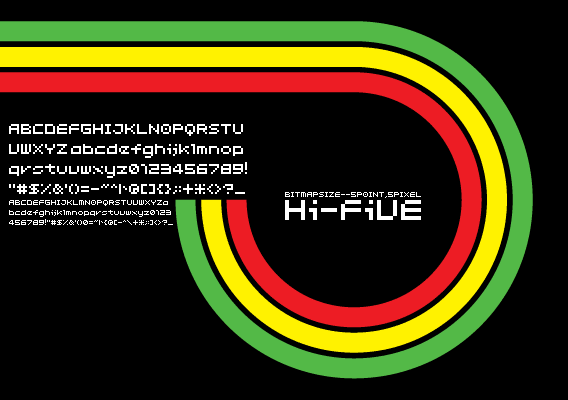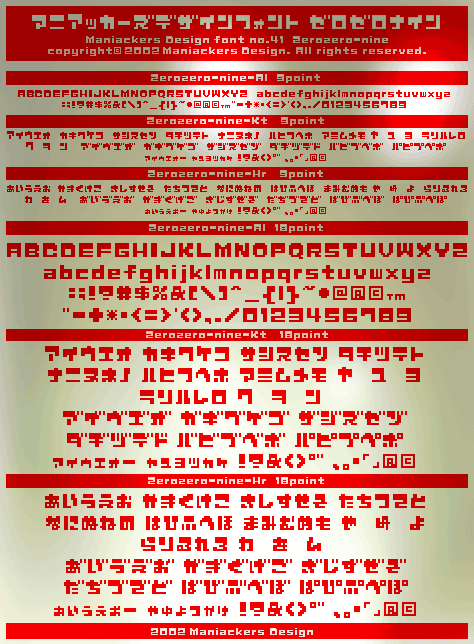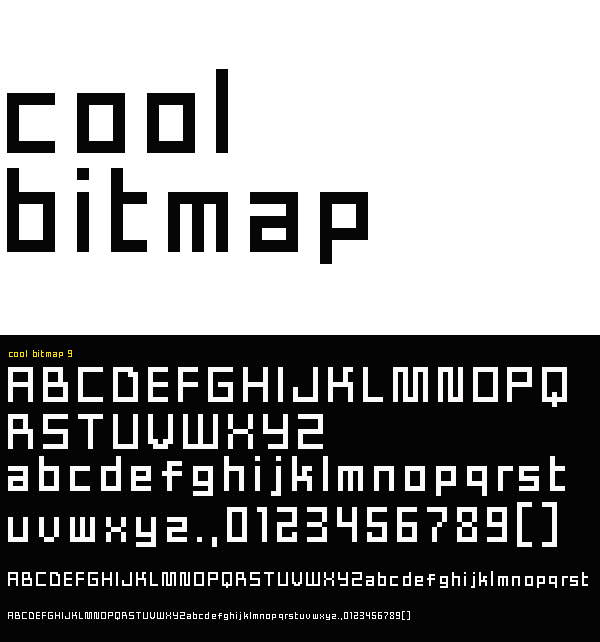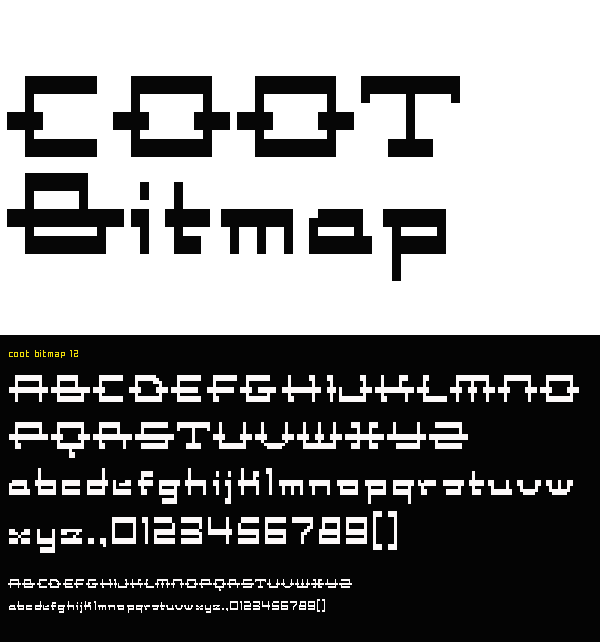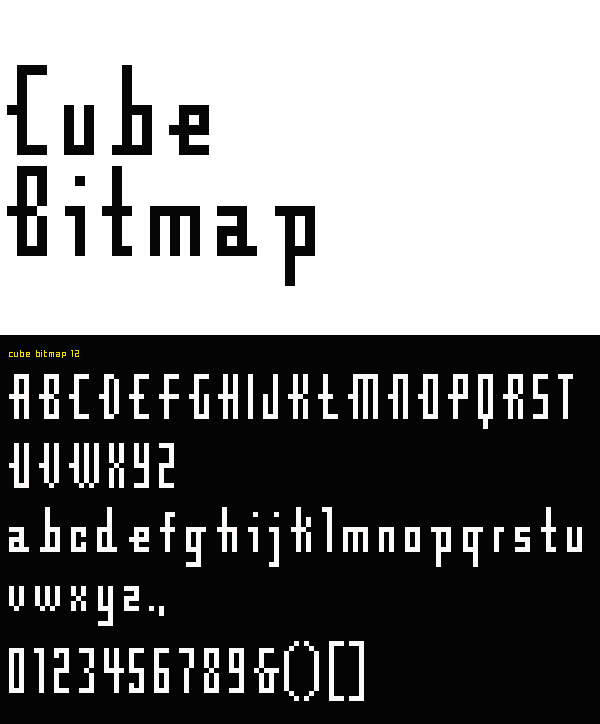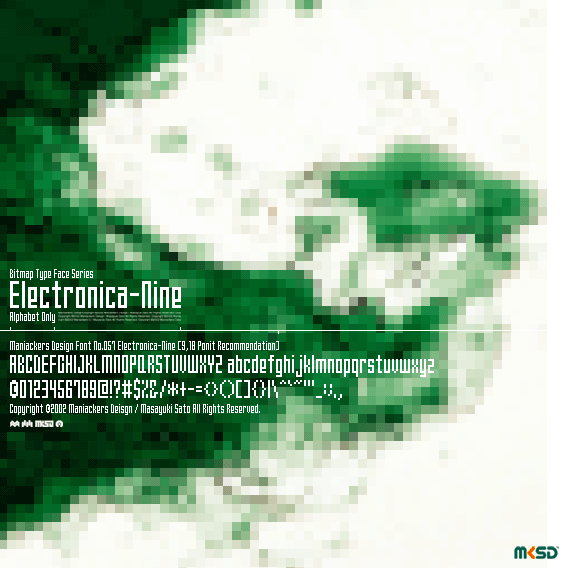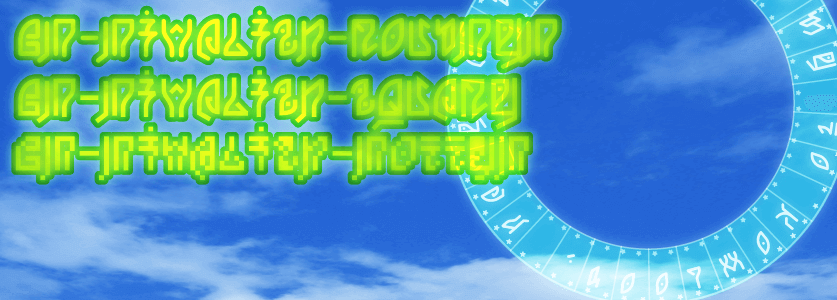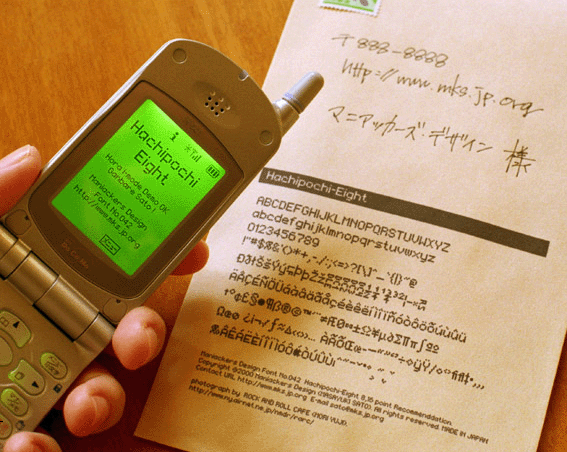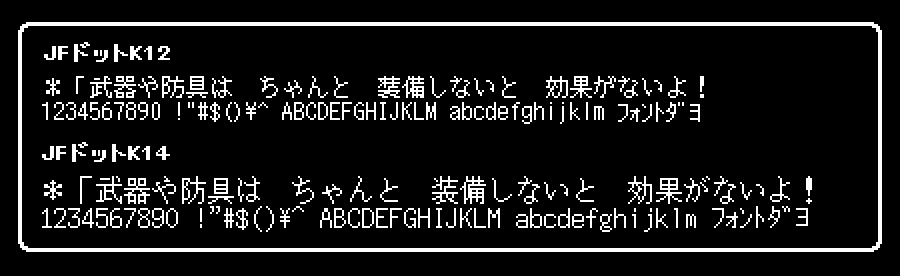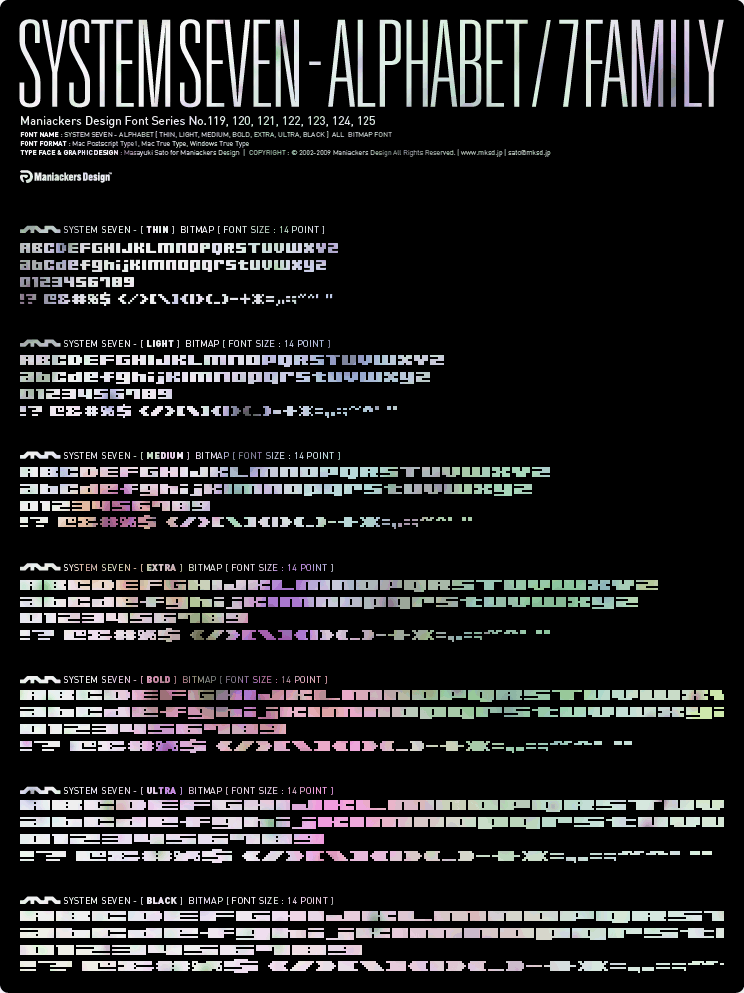
フリーで使える!ビットマップフォント86種類のまとめ
見やすいビットマップフォントをフリーでダウンロードできるサイトを86種類ご紹介します!ビットマップフォントとは、コンピュータ上で文字を表現する形式の1つで、文字を点(ドット)の集合体として表現したフォントです。同じビットマップフォントでもそれぞれに個性があるので使用したい目的に合わせてじっくり確認してからお使いください。
4×4極小かなフォント
縦横4ドットというわずかな空間に作られた芸術的なフォント。
AK-Akubit 12H
12px使用推奨の1バイトカナフォント。ひらがなver。
AK-Akubit 12R
上記フォントのカタカナver。
AMIフォント
古いPCの画面で使われているようなフォントを再現できるフォント。
Cask bit
カクカクとしたデザインが特徴のビットマップフォント。
Celer kana bit
横につぶれた感じのビットマップカナフォント。
Cheese bit
ゲームの画面で使えそうなビットマップ英字フォント。
Chibit
かわいらしいビットマップフォント。
Comdot Series
縦に伸びたアルファベットのビットマップフォント。
Cool bit
かっこよく見やすい英字フォント。
coopchick
ヒヨコなビットマップフォント。1バイトカタカナ。
coopchick 3D
立体的なビットマップ風フォント。アンチエイリアスオフで使用することを推奨。
coopchick bold
太めのビットマップ風フォント。アンチエイリアスオフで使用することを推奨。
coopchick edge
ふちどりされているビットマップ風フォント。アンチエイリアスオフで使用することを推奨。
coopoppo
はとぽっぽなビットマップフォント。
coopoppo 3D
coopoppoの3Dバージョン。
coopoppo bold
coopoppoの太めバージョン。
coopoppo edge